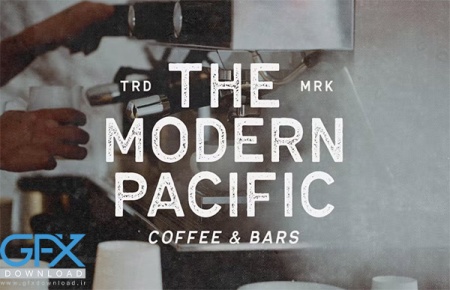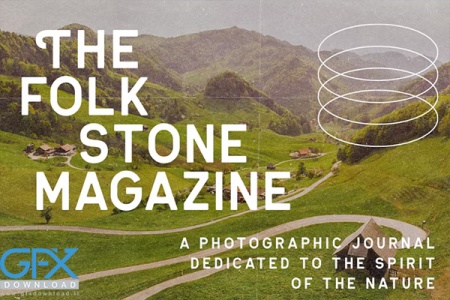
فونت پررنگ انگلیسی رایگان Break Shot
دانلود فونت پررنگ انگلیسی رایگان Break Shot
دانلود رایگان فونت پررنگ انگلیسی Break Shot
یک فونت پررنگ و بسیار جذاب. این نوع فونت کاملا ساخته شده است که نیاز به یک فونت برجسته و سایر اشکال رسمی مختلف مانند دعوت نامه، برچسب، لوگو، مجلات، کتاب، کارت تبریک/عروسی، بسته بندی، مد، آرایش، لوازم التحریر، رمان، برچسب یا هر نوع دیگری دارد. فونت پررنگ انگلیسی رایگان Break Shot برای انواع اهداف تبلیغاتی مناسب است.
فونت رایگان پررنگ انگلیسی Break Shot
فونت رایگان پررنگ Break Shot
• نام فونت: Break Shot
• با اعداد و علائم نگارشی
• چند زبانه
• لیگاتورها رمزگذاری شده PUA